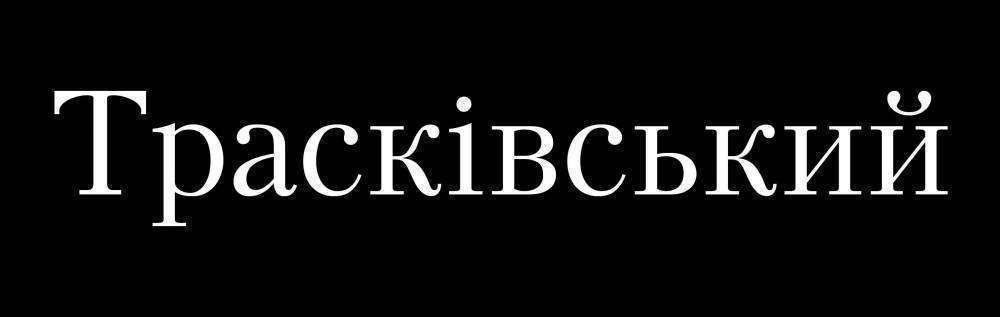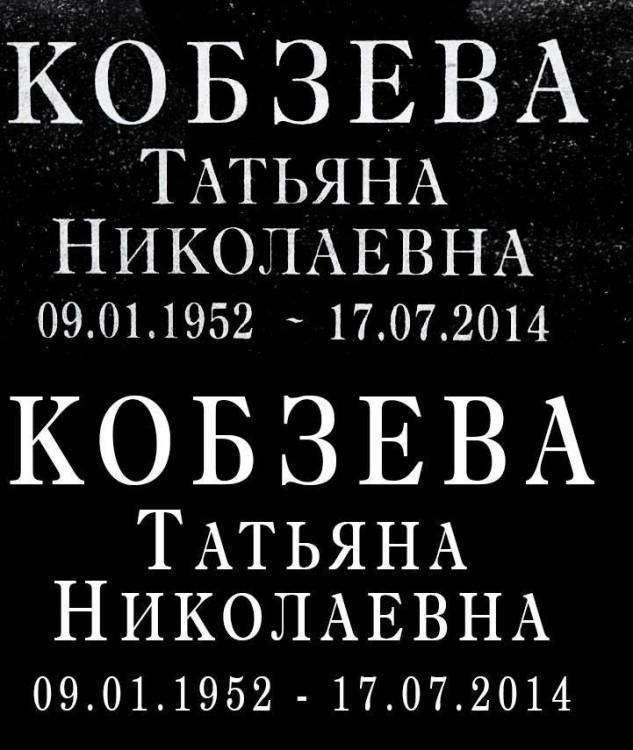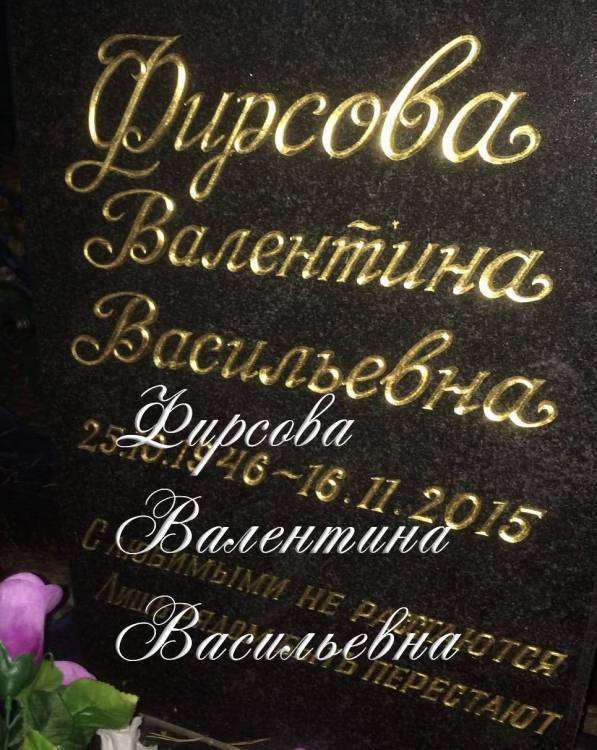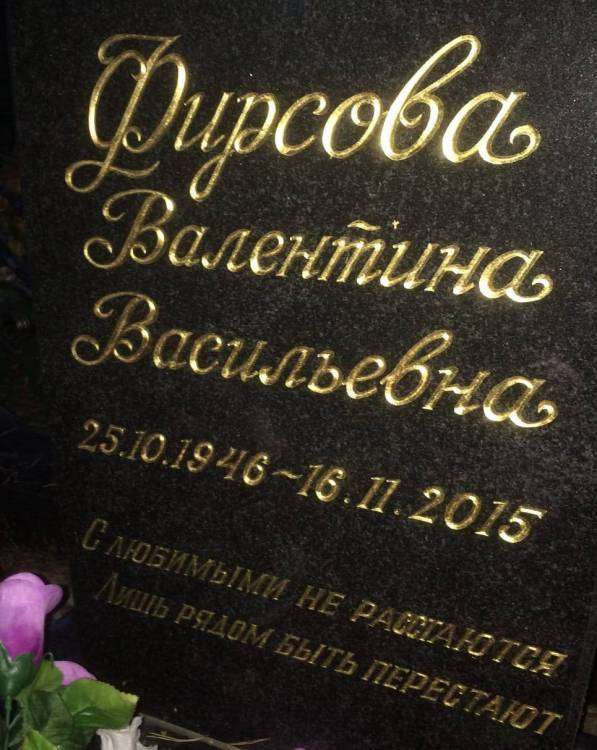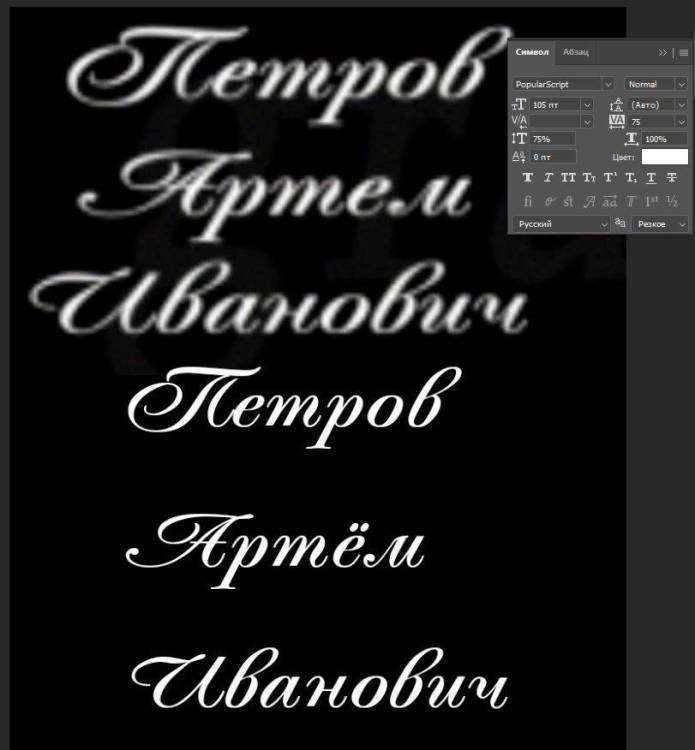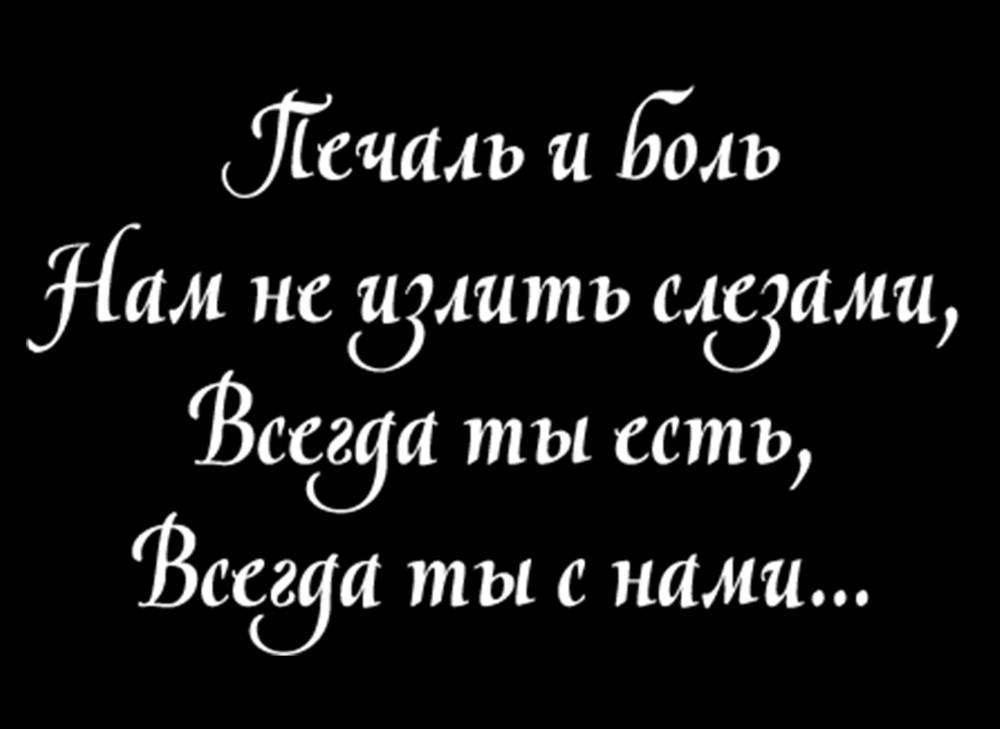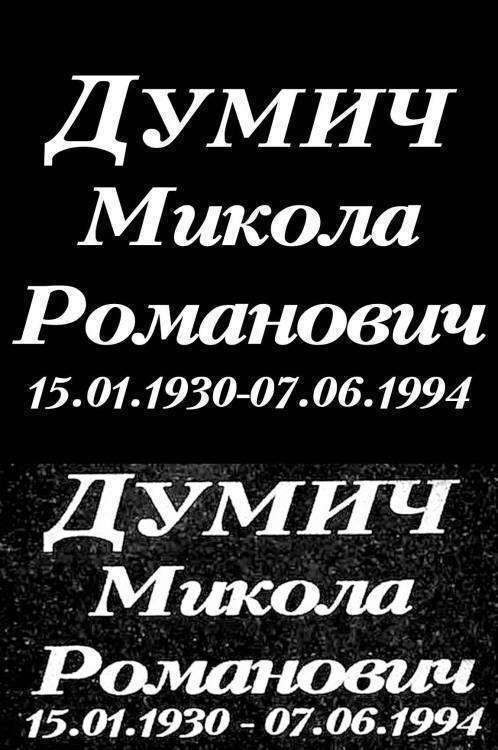
Помогите найти шрифт!
Помогите пожалуйста найти похожий или этот шрифт
Здравствуйте. Подскажите пожалуйста что за шрифт? Или может есть у кого-то похожий.
Шрифт называется "Izgoleniya". Весьма популярен, но ввиду своей уникальности найти его практически невозможно. Как вариант, можно попробовать потискать потиснить, слегка (лишь бы не дОсмерти) испортив "Antonellу". Если сильно постараться, что-то может получится.
Рукописный.
Обрати внимание на различия в начертании букв "р", "а", "е"...
Привет, помогите, пожалуйста. Автоопределение не помогло...
P.S. блиин, только досмотрел, что он ручной))
Аналоги не посоветуете?
Помогите определиться со шрифтом
Текст похож на a_AntiqueTrady
цифры на CentSchbkCyrili BT
ПОдсобите со шрифтом ... что за зверь???
@ПавелСерп больше всего похоже на CyrillicUniversity.
Нашелся точь в точь a_Romanus Regular https://ofont.ru/view/507
@ПавелСерп или a_Romanus
Ну да. С обводками поупражняться только. Либо белая снаружи, либо чёрная внутри. Либо как-то ещё)))
Доброе утро. подскажите пожалуйста шрифт название или близко к токому варианту похожий. что бы был с завитушкой и не тонкий
кто знает название шрифта?
помогите с названием шрифта
помогите пожалуйста со шрифтом. был-потеряла, :dontknow:найти не могу(((